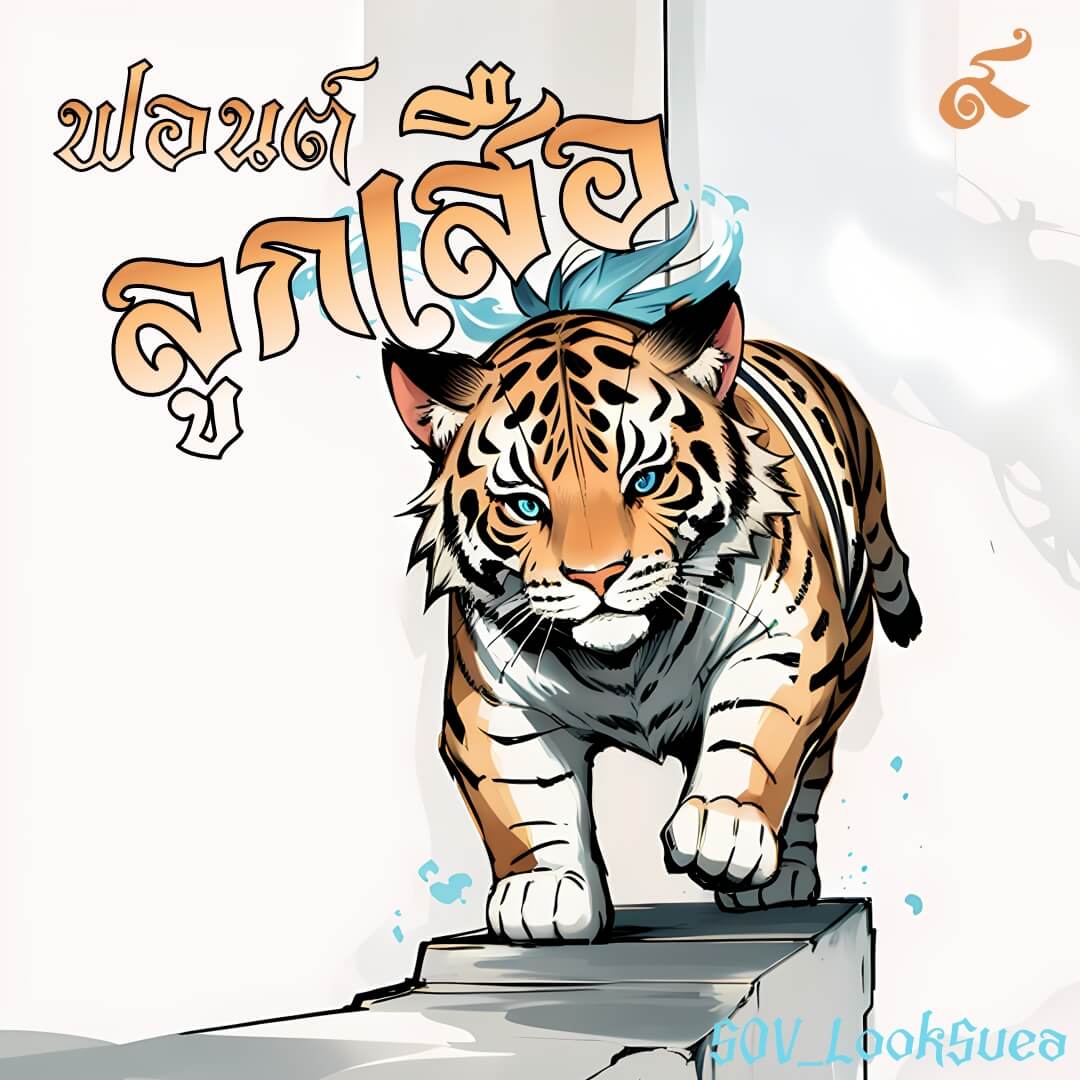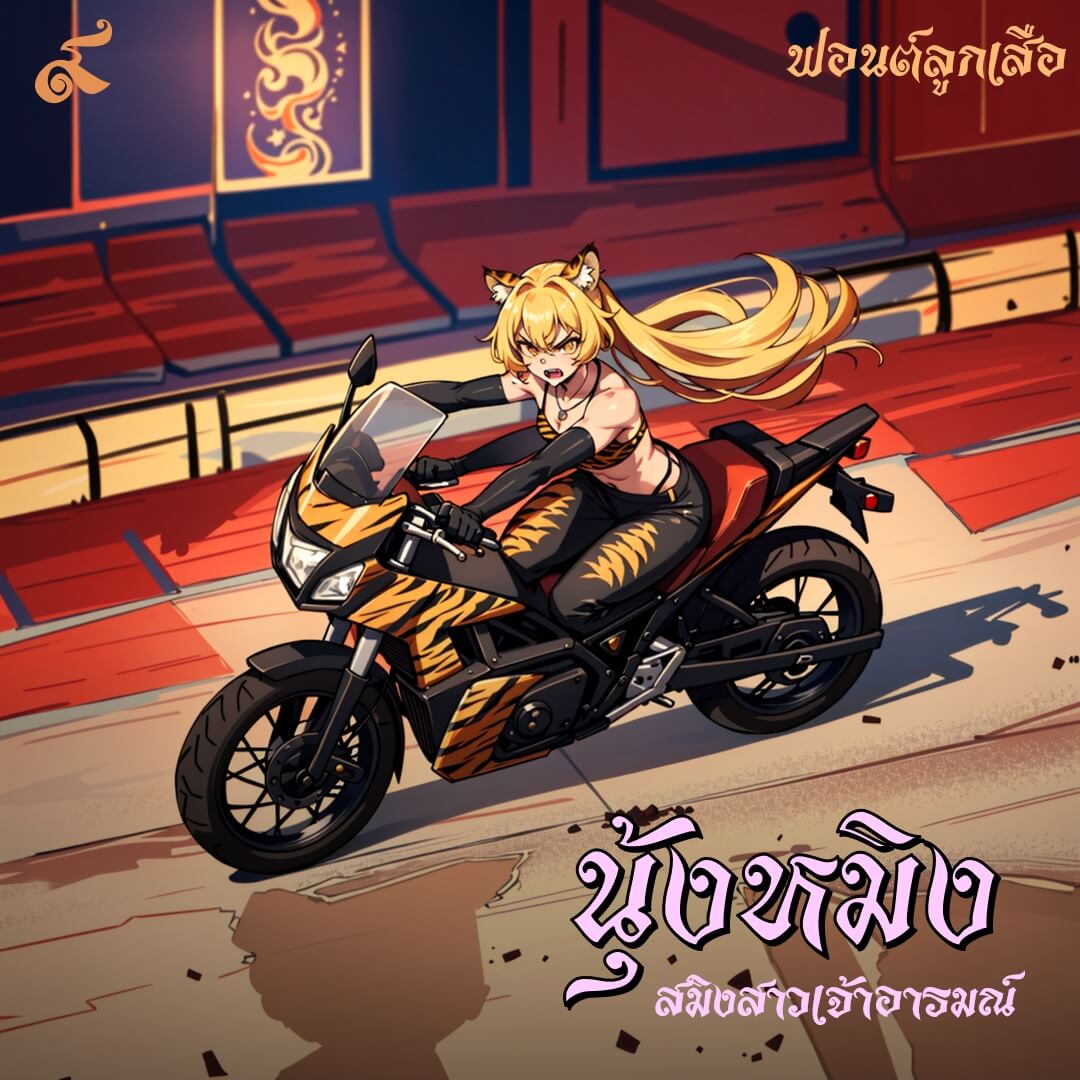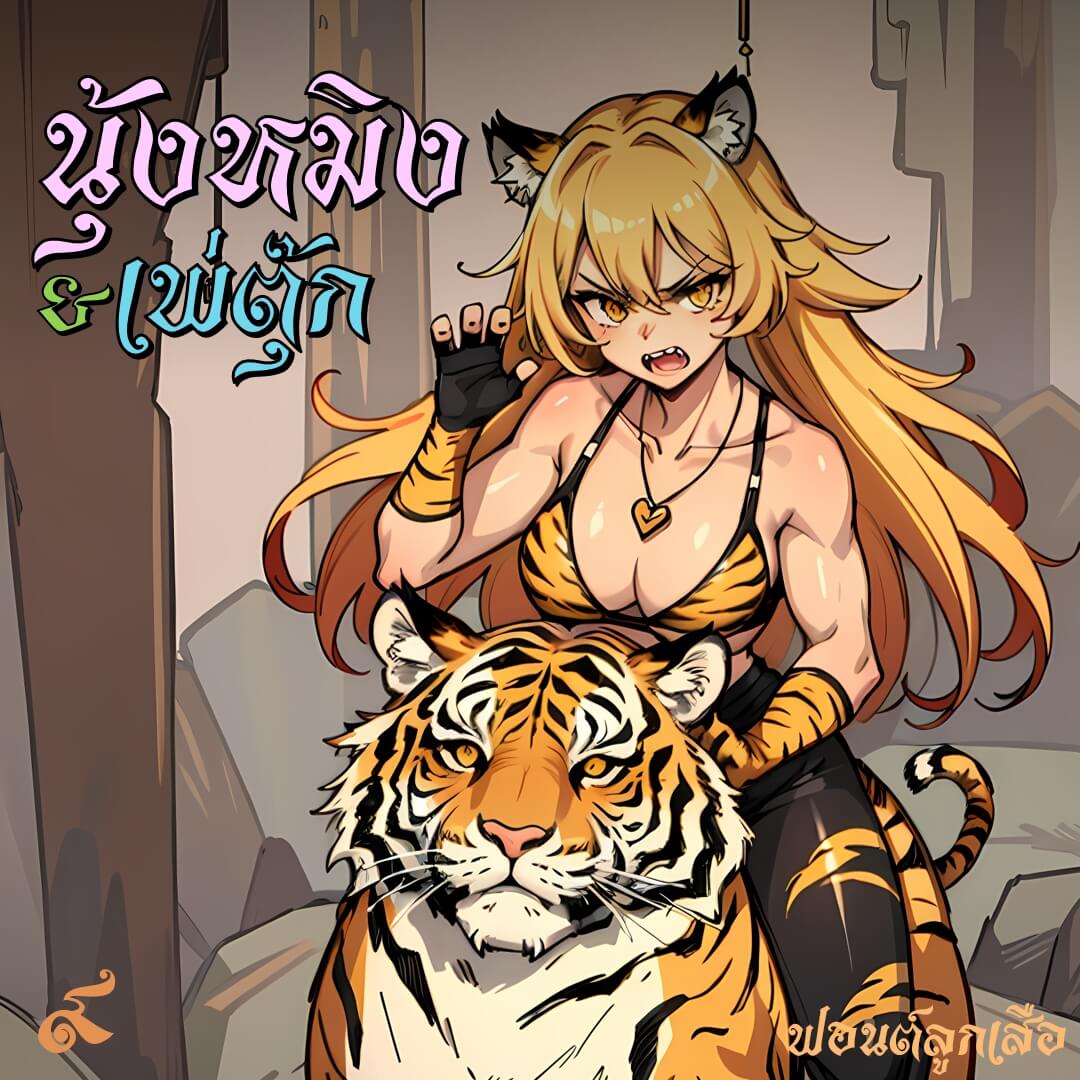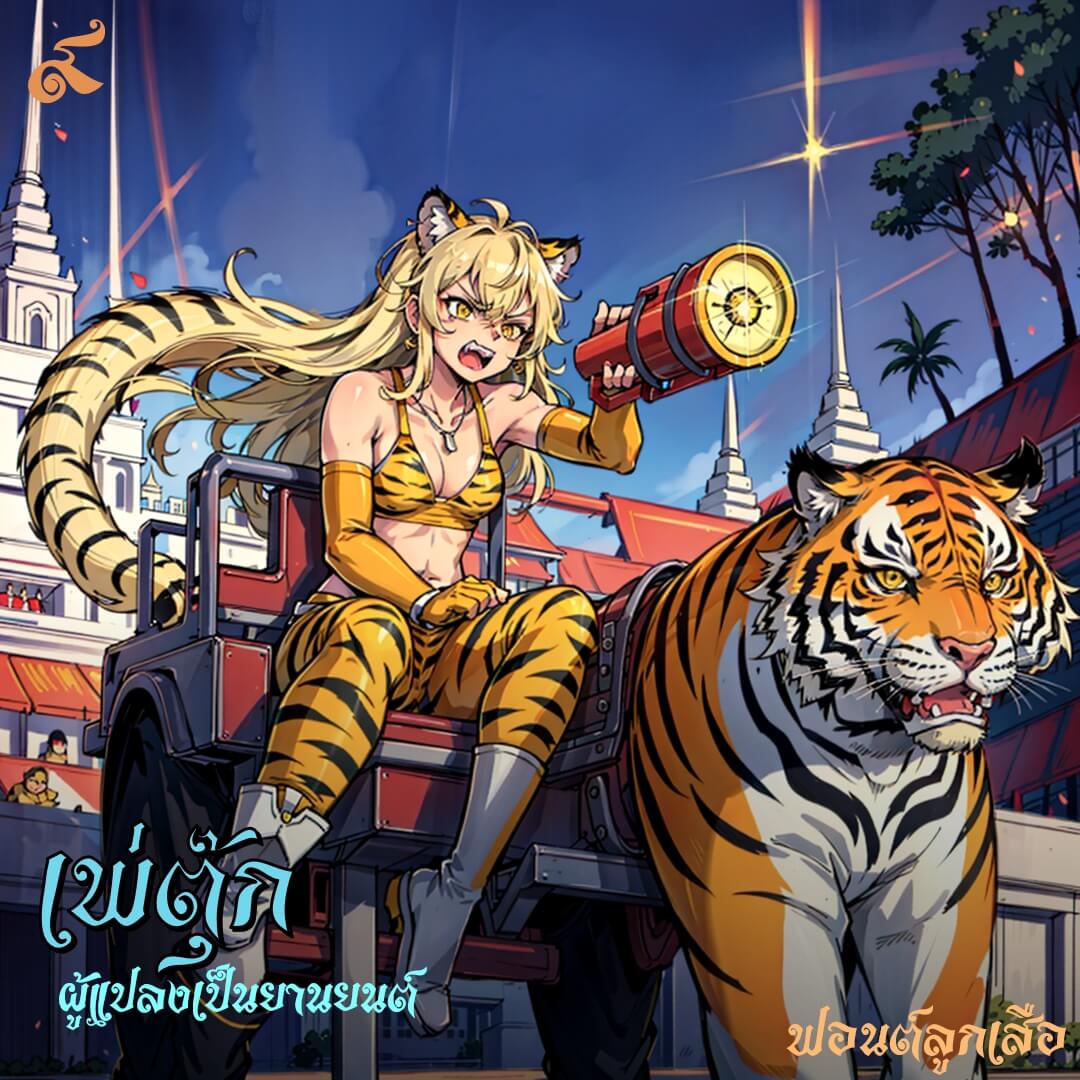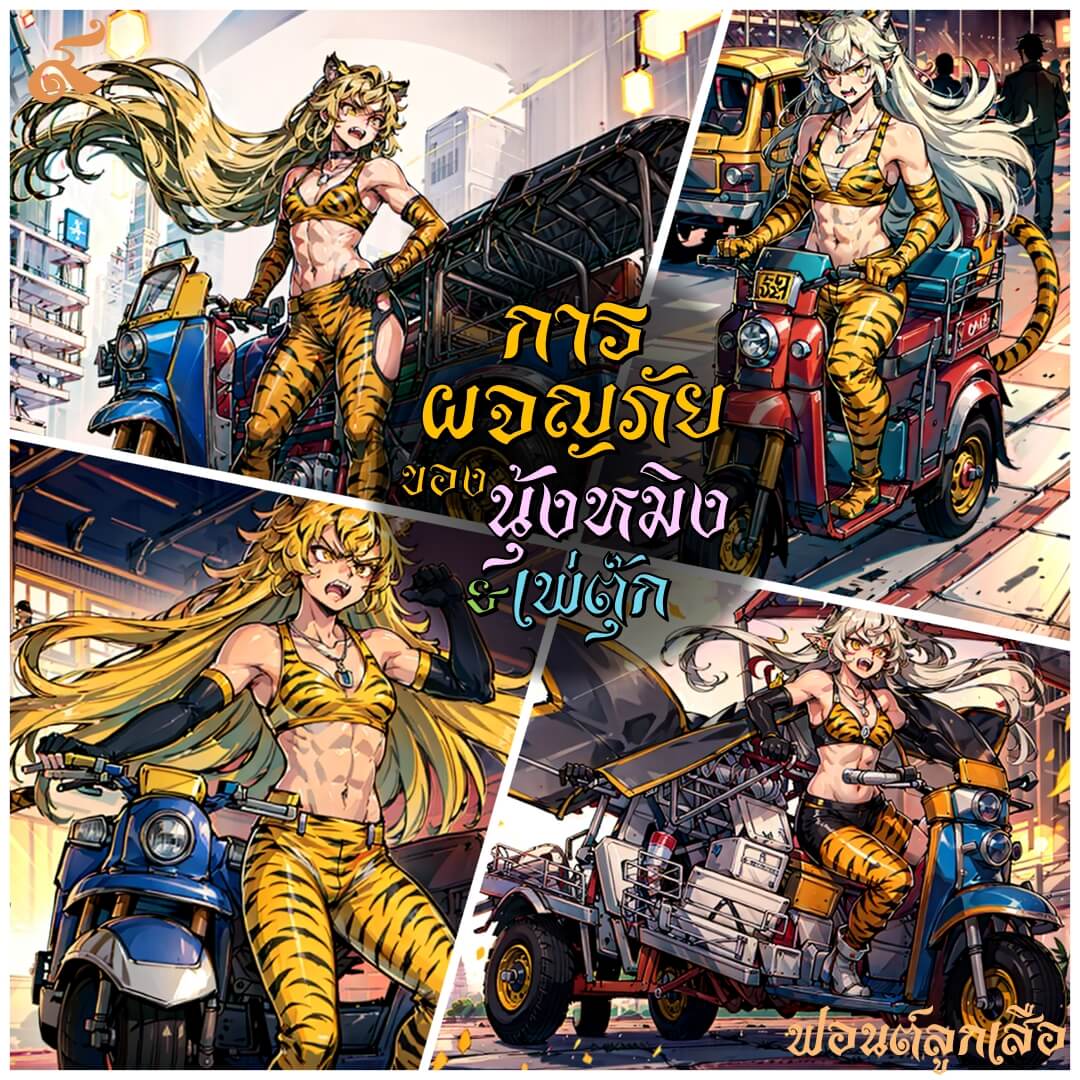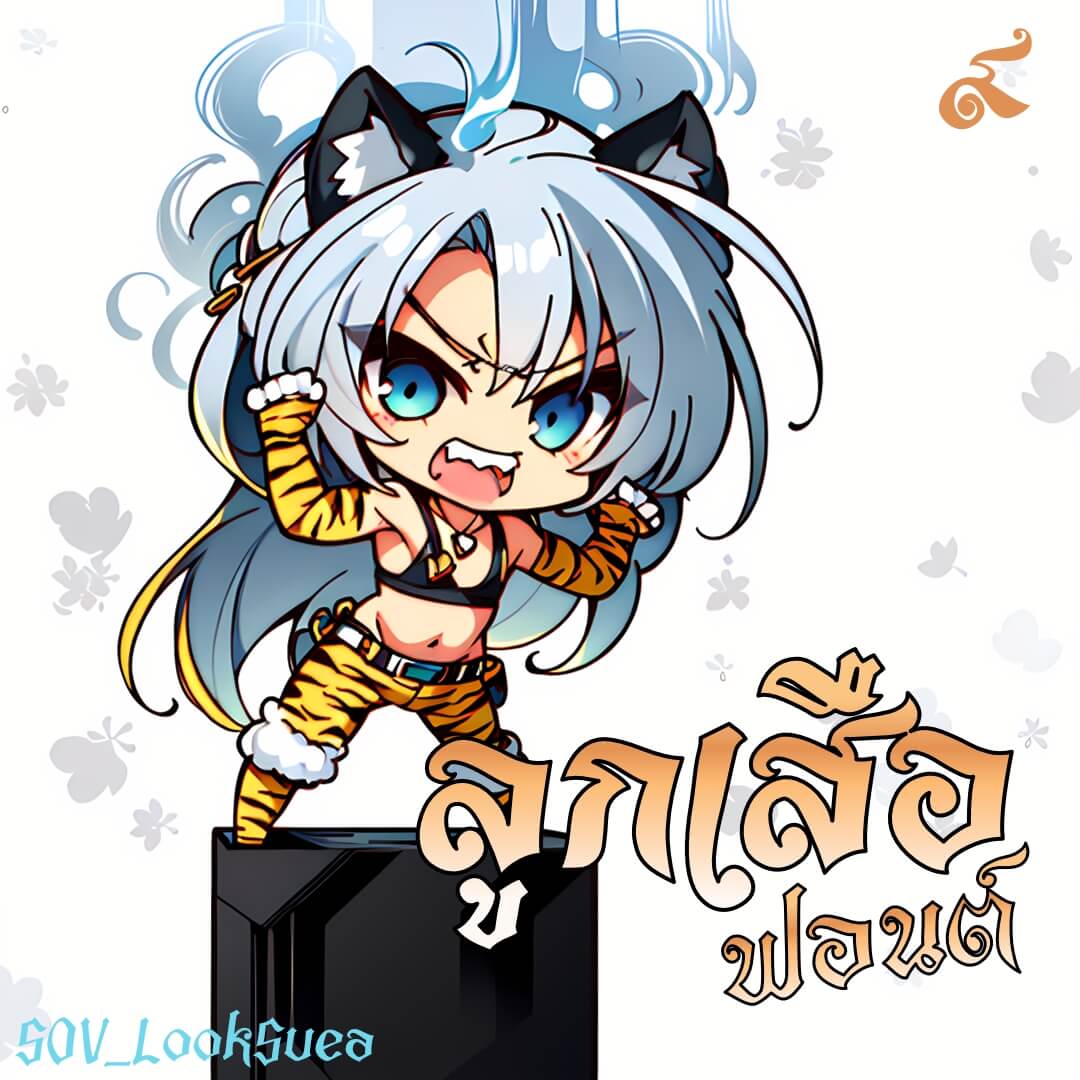
ฟอนต์ลูกครึ่ง แนวคิดจากตัวเชิงอักษรละตินอวบๆ ปรับเป็นอักษรไทย เปลี่ยนใจเอาเชิงออก บางตัวจะกลมก็ปรับเป็นเหลี่ยม ไม่เอาสักทาง ส่วนภาพประกอบทำได้ทุกอย่างเพราะน้องเป็น AI เน้อ ไม่ใช่ภาพคนจริงๆ
ลูกเสือ (SOV_LookSuea)